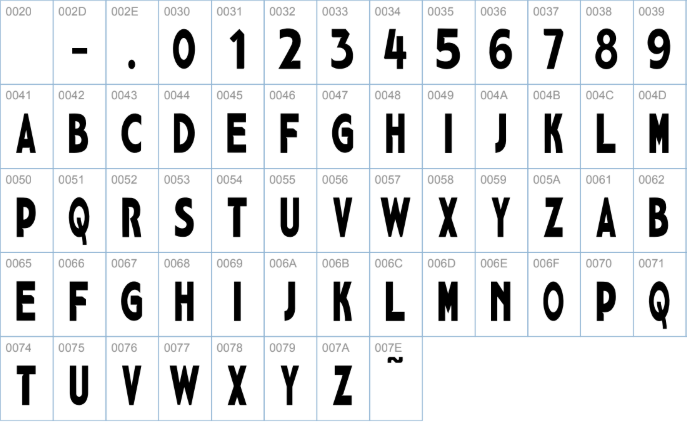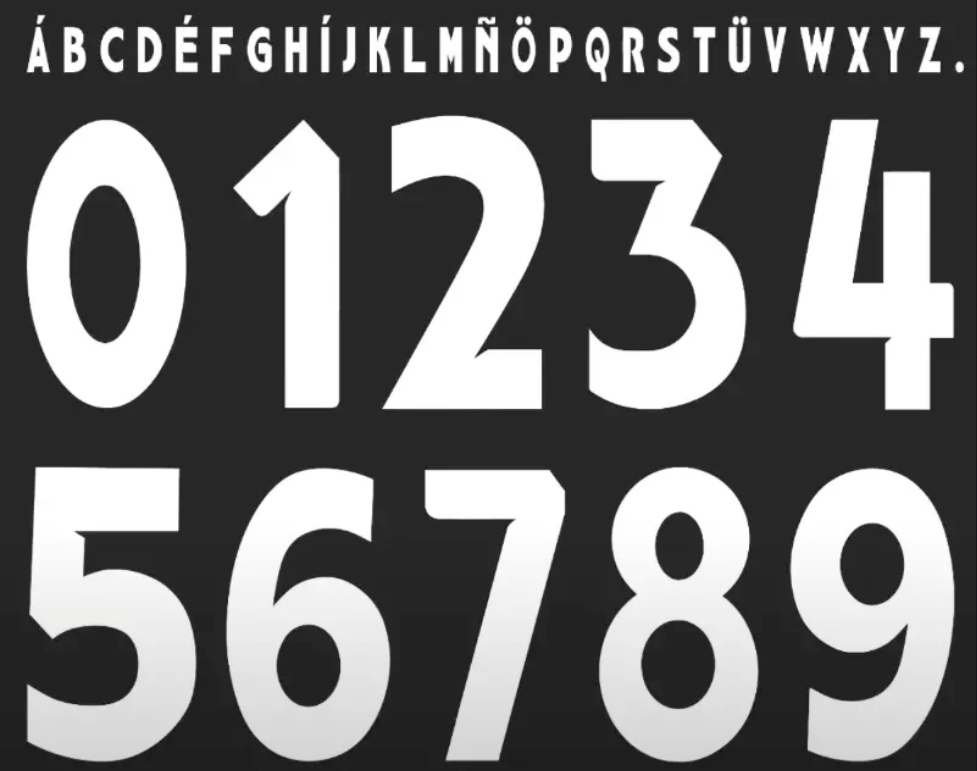
Se você está procurando a tipografia perfeita para criar réplicas, mockups ou personalizar aquela arte especial do Vascão, você chegou ao lugar certo. Hoje trazemos para download a fonte utilizada nos uniformes do Vasco da Gama para a temporada 2024.
Esta é a tipografia que estampa as camisas produzidas pela Kappa, vestindo os jogadores em São Januário e em todos os estádios do Brasil. Seja para estampar o nome de ídolos como Payet e Vegetti, ou para colocar o seu próprio nome no manto, ter o arquivo correto faz toda a diferença no resultado final.
Estilo Visual e Identidade
A fonte do Vasco da Gama 2024 reflete a tradição e a imponência do clube. Diferente de fontes genéricas, a tipografia desenvolvida para a parceria com a Kappa possui traços sólidos e angulares, garantindo excelente legibilidade tanto na camisa negra (Home) quanto na branca com a faixa diagonal (Away).
O design dos números costuma trazer detalhes sutis que remetem à herança náutica e histórica do clube, mantendo um visual moderno e limpo. É a escolha ideal para quem deseja criar estampas de camisas de futebol (fardamentos), banners para redes sociais ou projetos de sublimação que exigem fidelidade ao material oficial de jogo.
- Conteúdo: Alfabeto completo (caixa alta) e numeração oficial de jogo (0-9).